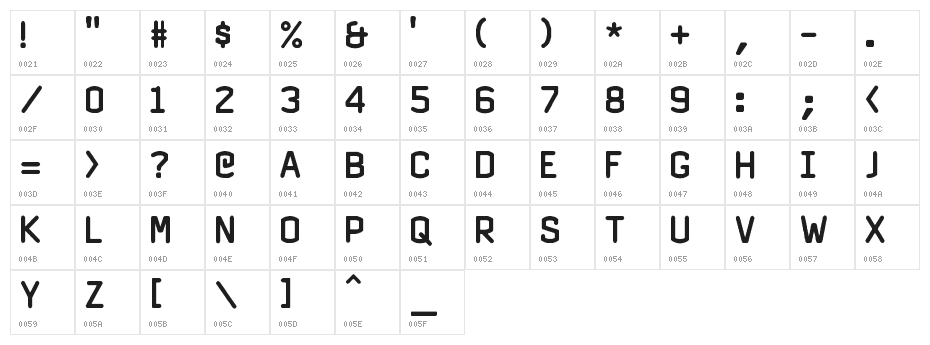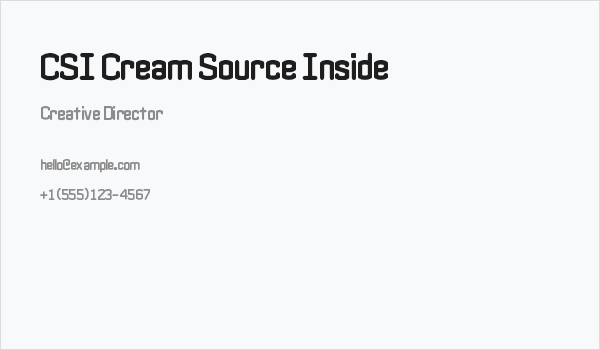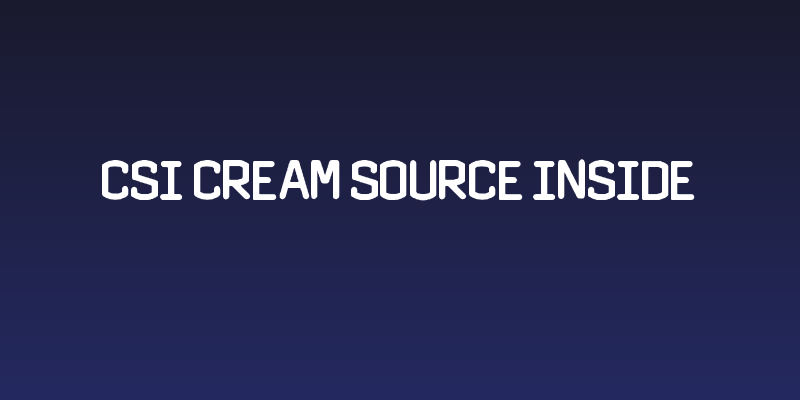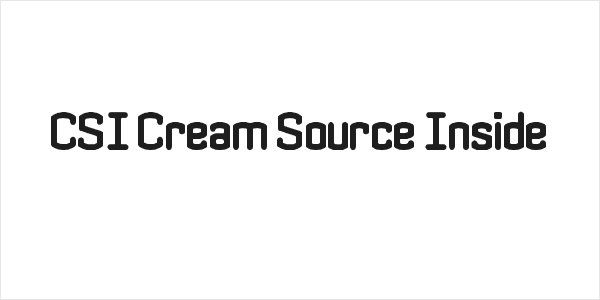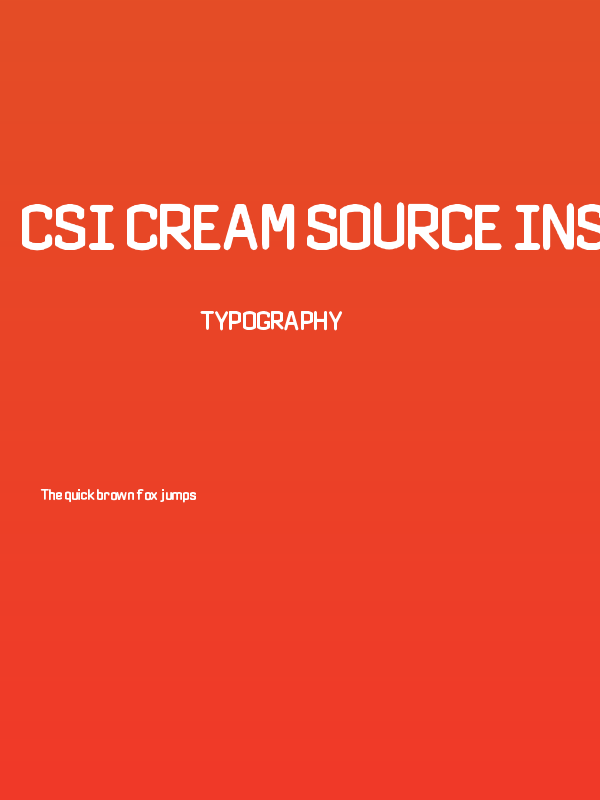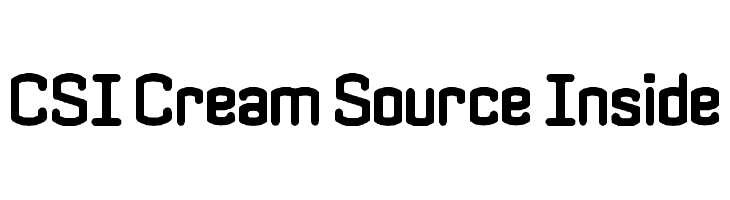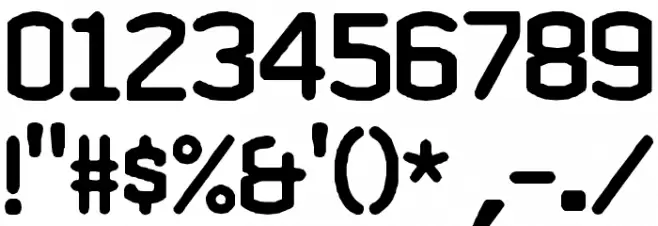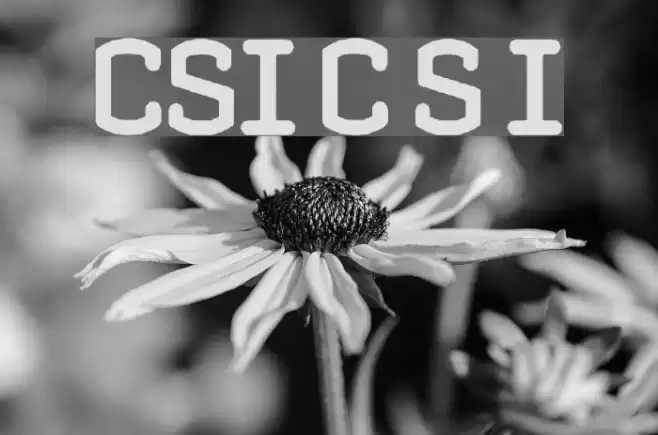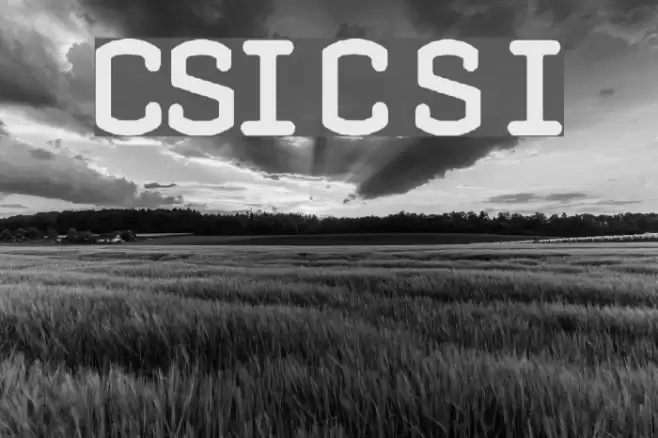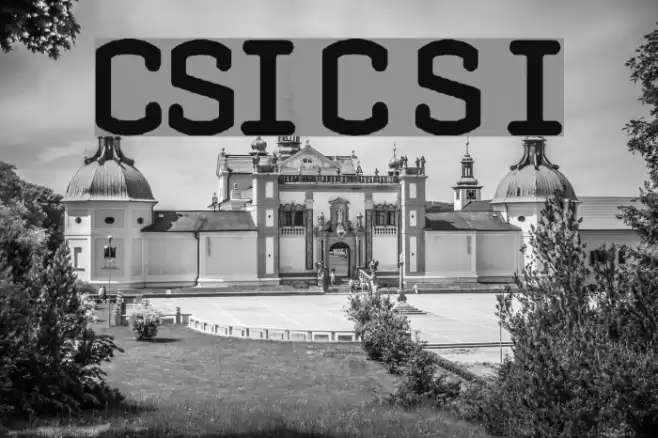
CSI Cream Source Inside Font
| الاسم | CSI Cream Source Inside |
| مشاريع مقترحة | Ideal for children's books, playful branding, casual invitations, and digital content aimed at a younger audience. |